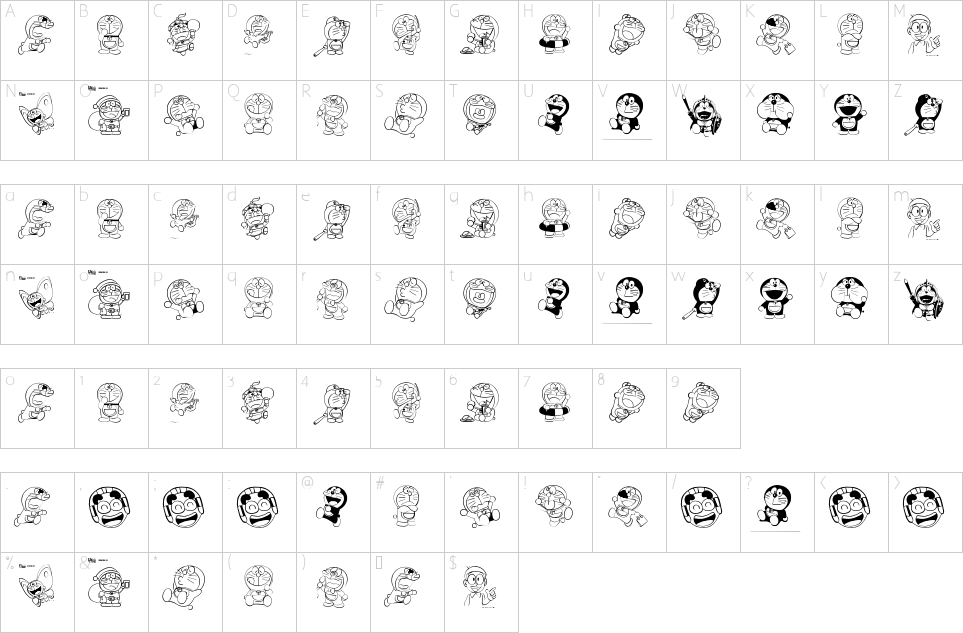
Doraemon Slalala Font – Download Grátis
A fonte Doraemon Slalala é uma criação amigável criada por Docallisme HAS – Ryal, disponível para download tanto no Windows quanto no Mac. Esta fonte incorpora os elementos vibrantes e alegres do personagem Doraemon em cada letra, trazendo um toque único de descontração ao seu design. Com mais de 3 mil downloads, é evidente que esta font conta com uma recepção positiva por parte dos usuários. Se você está procurando por algo divertido e colorido para adicionar aos seus projetos gráficos, Doraemon Slalala pode ser a escolha perfeita. Além de oferecer um toque jovial, também tem o benefício de ser altamente customizável, permitindo que você personalize seu design sem sacrificar a harmonia visual.